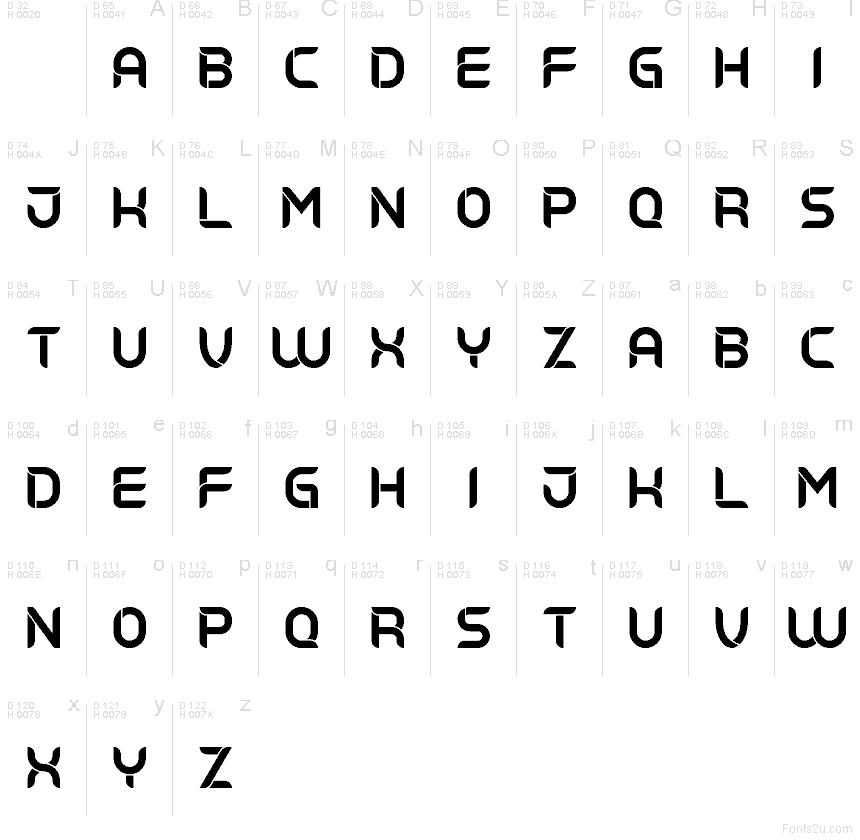
Belgrado Flat, moderné bezplatné písmo od Vladimira Nikolića, premieňa geometrické tvary písmen na plynulý, prepojený rytmus. Znaky pôsobia široko a technicky, s hrubými ťahmi, štvorcovými rohmi zjemnenými širokými krivkami a spojeniami, ktoré vytvárajú dojem slova ako jedného aerodynamického celku.
Hodí sa na branding, titulky na plagátoch, obaly albumov, dizajn obalov a úvodné titulky, kde kompaktná sadzba potrebuje futuristický nádych bez toho, aby pôsobila ako čistá sci-fi. Ako bezplatné písmo sa skvele hodí aj na krátke nadpisy, logá a monogramy, pretože opakujúce sa zaoblené rezy a horizontálne mostíky dodávajú aj niekoľkým písmenám silnú a ucelenú vizuálnu prítomnosť.
„Belgrado“ je k dispozícii vo verziách Regular a Italic.
Obsahuje srbské znaky cyriliky.